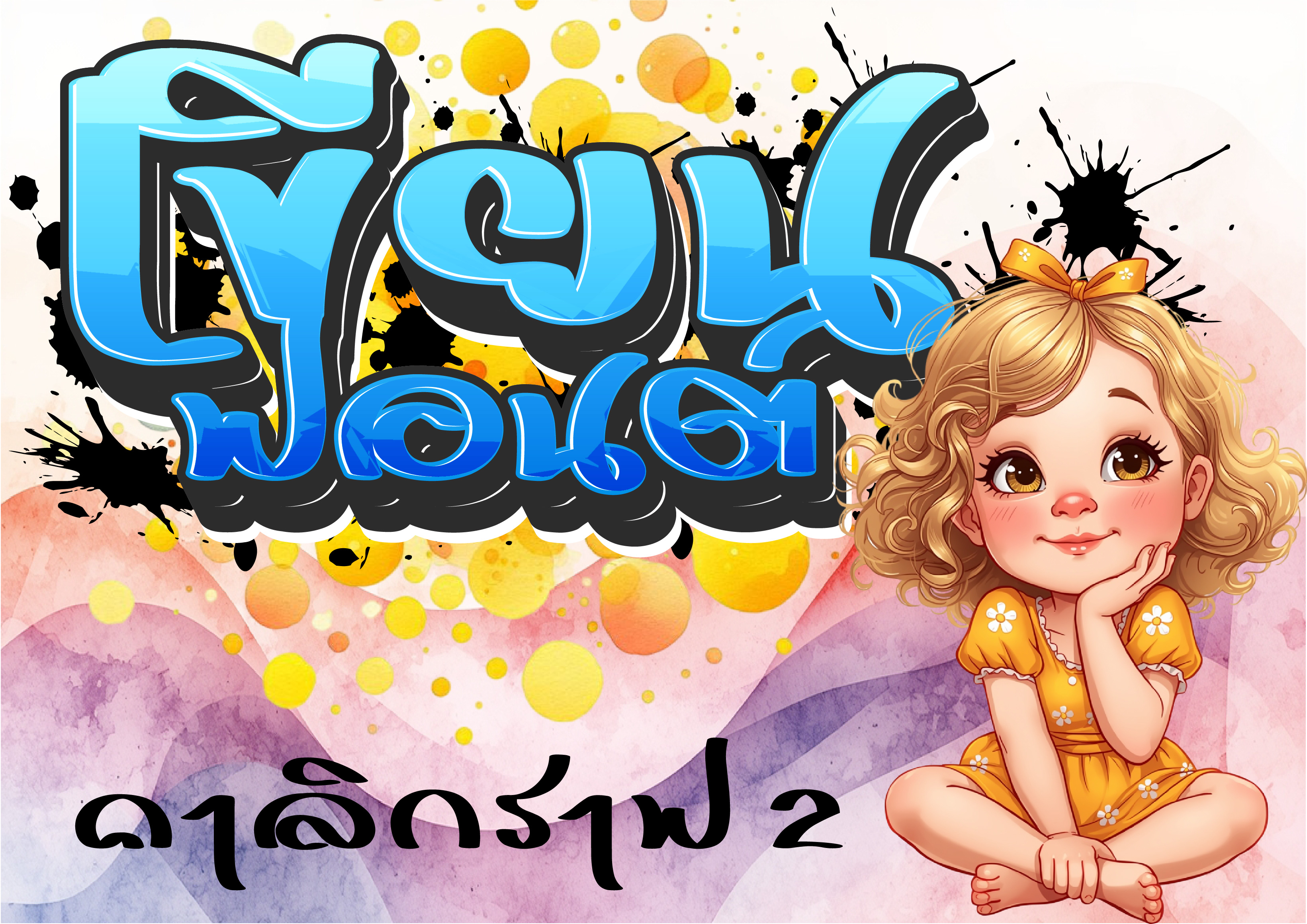
พิกัดฟอนต์
พิกัดฟอนต์ซันนี่ (PKF-sunny)
Wendysfontstore
ฟอนต์ "ทอศิลป์ ยอดฝีมือ"
เป็นฟอนต์รูปแบบสไตล์จีน
เลียนแบบการเขียนพู่กันจีน
ออกแนวยุทธภพ จอมยุทธ
ทำมาสองน้ำหนัก ปกติ และหนา
KirakiraFontverse
บ้านน.fonts
ฟอนต์ลายมือ
ชื่อฟอนต์ : เกรกก์ไทย
ฟอนต์เกรกก์ไทย เป็นฟอนต์ทดลอง อักษรชวเลขแบบเกรกก์ ทำเสร็จไป 80% แต่คิดว่าพอก่อน..
ตัวอักษรไม่มีความกว้างต้องเคาะ space ให้เลยตัวอักษรที่เห็นเอาเอง และต้องศึกษาชวเลขก่อน ส่วนการอ่านถ้าชวเลขยังไม่คล่องใช้ตัวปรกติ ถ้าคล่องแล้วใช้ตัวหนา(กด bold)
TCHA STUDIO 23
ฟอนต์ลายไทย (TCS4LaiThai)
พิกัดฟอนต์
พิกัดฟอนต์วิวิด (PKF-vivid)
พอ จะ นะ
SP_KhianFont เขียนฟอนต์